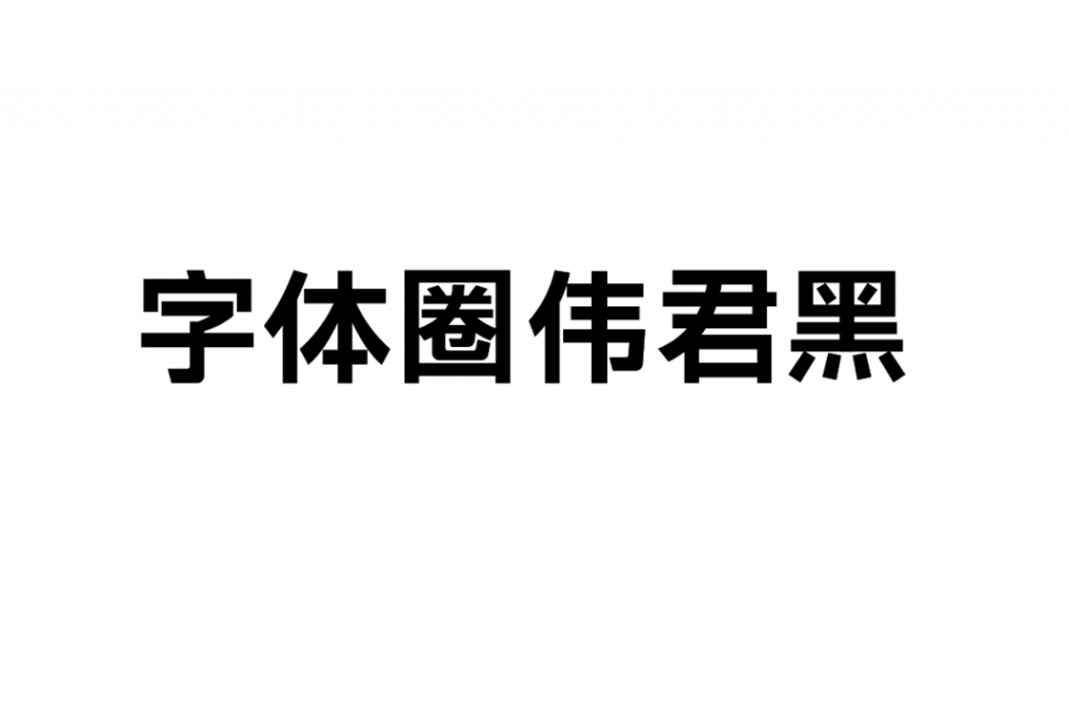
字体圈伟君黑是由邹乐伟于微信公众号字体圈(公众号ID:fontquan)发布的一款中文免费商用字体。
字体圈伟君黑字体有W1、W2、W3三个字重,适合多场景使用,例如正文排版、标题设计等,基本能用到字体的地方,都可以使用我们的《字体圈伟君黑》,字库现包含6763个汉字及若干个符号等,总字符7000余。